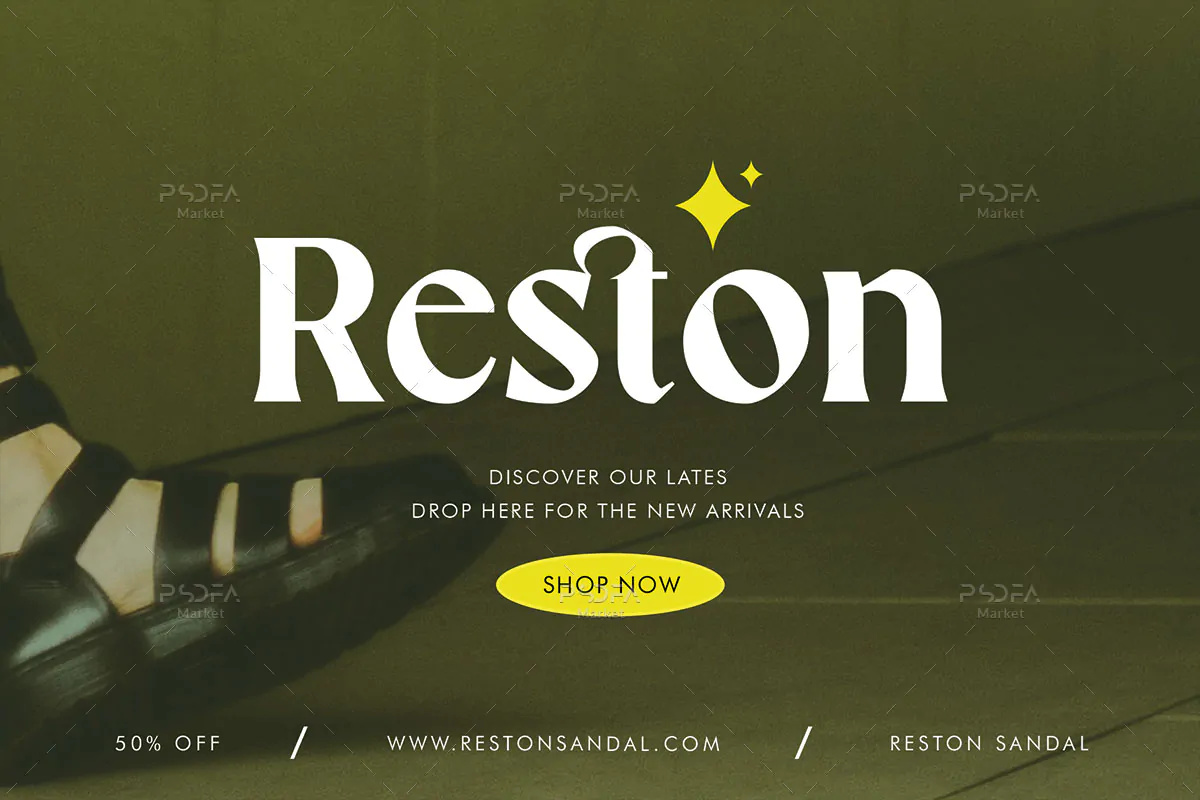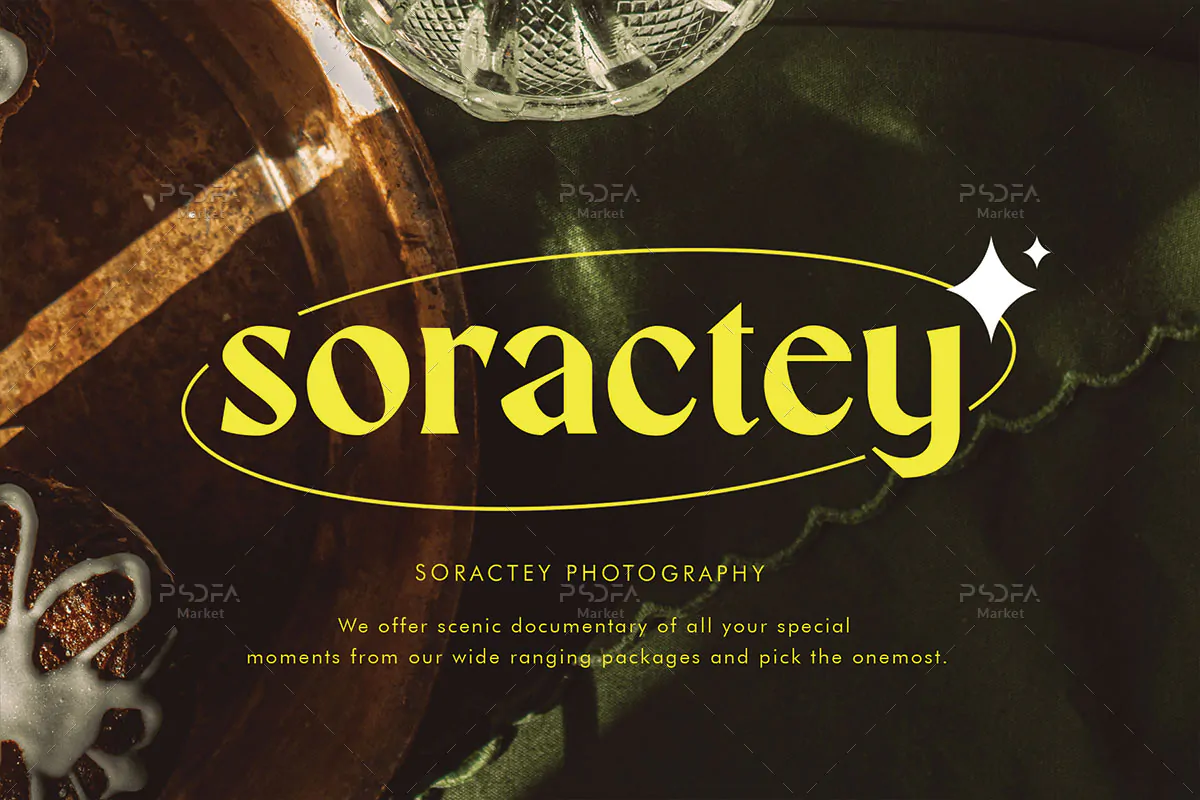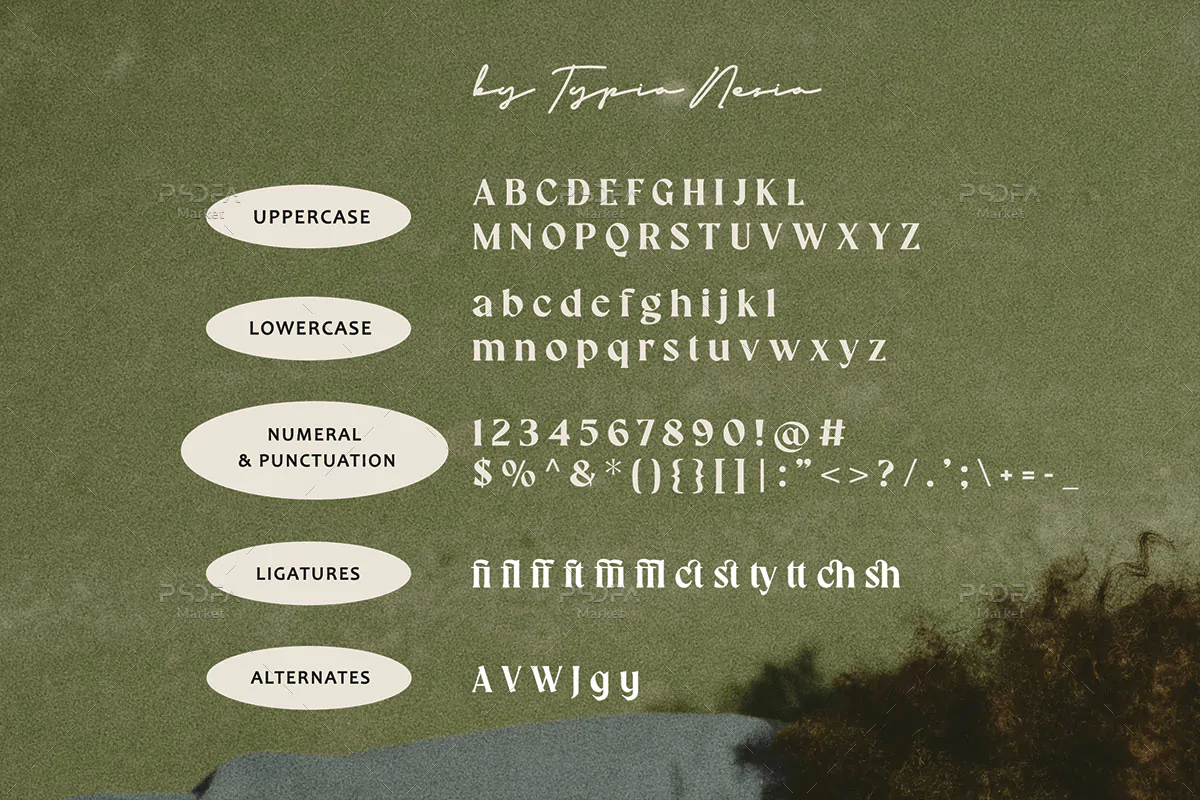
سریف فونت رترو و قدیمی Salty Ages
سریف فونت رترو و قدیمی
سریف فونت رترو و قدیمی Salty Ages یک قلم فوق العاده زیبای انگلیسی است که مناسب جهت استفاده در طرح و پروژههای گرافیکی مختلف میباشد. فونت Salty Ages با وزن معمولی طراحی شده است که میتوانید از آن در طراحی پوستر، کارت ویزیت، تراکت، بروشور، کتب و مجلات، بسته بندی محصولات، طراحی صفحات وب و … استفاده کنید.